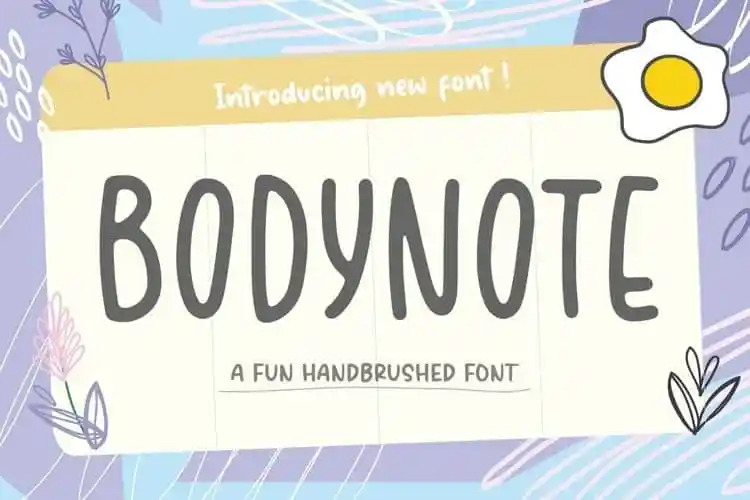
BODYNOTE Fun Handbrushed Font – Download Grátis
A fonte BODYNOTE Fun Handbrushed Font é perfeita para criar uma atmosfera envolvente e natural ideal para aplicar em diversos projetos digitais. Seja para embalagens de produtos, criação de marcas, revistas, mídia social, casamentos ou apenas expressar palavras acima de um fundo, ela se encaixa perfeitamente. Com sua arte manual desenhada com paixão e detalhes cuidadosos, a fonte BODYNOTE Fun Handbrushed fornece o toque especial que suas criações digitais merecem. É uma escolha versátil para qualquer projeto que deseje transmitir um estilo único e pessoal através de textos e imagens.